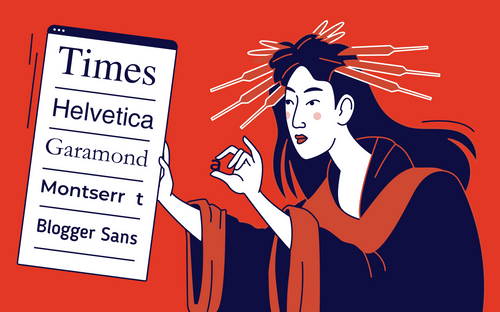
Какой шрифт лучше для чтения
Лучшие шрифты для чтения на электронной книге eBook
При чтении электронных книг приходится проводить много времени уставившись в экран. Поэтому внешний вид текста имеет большое значение! Правильный выбор шрифта может улучшить общее впечатление от чтения. Какой шрифт поможет вам читать быстрее и меньше напрягать глаза? Когда речь заходит о шрифтах, выбор очень велик. Некоторые шрифты приятны для глаз, некоторые обладают индивидуальностью, а некоторые легко читаются.
Если в вашей электронной книге много текста, самыми удобными для чтения будут шрифты с засечками, такие как Times New Roman, Garamond, Baskerville и Caslon. Эти старые традиционные шрифты уже давно используются для книг и по-прежнему являются отличным выбором для электронных книг. Важно, чтобы шрифт был удобен для чтения, тем более что люди будут читать его в цифровом формате на экранах любого размера. Шрифты с засечками более разборчивы и привлекательны для читателя.
Вот несколько лучших шрифтов, которые эксперты рекомендуют для электронных книг.
Какой шрифт лучше для чтения
Видео про саккады
Шрифты с засечками и без засечек одинаково «держат» строку
Хотя тут есть подвох. В тесте использовался шрифт 128 pt. Это в десять раз больше, чем в обычной книге, и, возможно, исследование не очень корректно применять к обычному процессу чтения.
Детские азбуки с первой страницы Гугла
Ученые взяли 80 детей 10 лет и 80 детей на два года старше, попросили их найти в тексте нужное слово (скрининг-тест) и измерили, как быстро у детей получилось это сделать.
Контрольной группе оба раза давали одинаковый шрифт, а экспериментальной — сначала шрифт с засечками, а потом без
Предпочтения же людей вообще однозначные: топ-3 шрифтов и у дислексиков, и у недислексиков — без засечек.
Разные типы сглаживания
Знаменитые дизайнеры vs научные исследования про читаемость шрифтов
Я работаю дизайнером около 10 лет. В дизайне не очень много объективных и проверяемых законов, и когда мне нужно было что-то выяснить, я искала информацию в профессиональных книгах, блогах крутых ребят, спрашивала у знакомых арт-директоров и приставала к людям в коридорах.
А потом узнала, что ученые уже сто лет как выяснили то, про что до сих пор спорят дизайнеры.
Мы в Тинькофф сравнили мнение знаменитых дизайнеров и ученых о том, какие шрифты легче читать: антикву(с засечками) или гротески(без засечек).
Почему я вообще этим занялась
Однажды мне нужно было написать инструкцию для джунов о том, как выбрать шрифт. Я написала, что для больших текстов лучше использовать шрифты с засечками, потому что глаза меньше устают от такого шрифта и засечки помогают держать строку.
Потом пришел редактор и откомментил: «Пруфы?»
«Да это же очевидно», — подумала я и открыла «Википедию»:
В «Википедии» пруфов не было, и я пошла к книжному шкафу.
На мой взгляд, шрифт с засечками меньше утомляет при долгом чтении обычных, «бумажных» изданий, чем гротеск, по двум причинам. Во-первых, засечки подчеркивают окончания штрихов, становясь дополнительными «смыслоразличителями». Во-вторых, буквы с засечками несколько сложнее по форме, поэтому сильнее отличаются друг от друга, чем гротесковые. А наш читательский глаз больше нуждается в балансе индивидуальности и унификации, чем дизайнерский, который радуется зеркальной вылизанности.
Юрий Гордон «Книга про буквы от Аа до Яя», Откуда взялись и зачем нужны засечки, стр. 51
Шрифт без засечек только кажется простейшим. Его форму специально упростили для детей, а взрослым его читать труднее, чем антикву, ведь ее засечки служат не только для украшения.
Ян Чихольд «Облик книги», О типографике, стр. 21
Ян Чихольд
Ну ладно, старинные мастера опирались на чутье, но, может, кто-то посовременнее объяснит с пруфами?
Сергей Сурганов, арт-директор «Медузы», дизайнер Notion:
Используйте шрифт с засечками для длинных текстов
Когда вы оформляете любой длинный текст (статью, резюме, письмо, инструкцию), стоит использовать шрифт с засечками, то есть антикву. Считается, что длинный текст, набранный таким шрифтом, легче читать. В традиционной книжной верстке тоже используются именно антиквы, поэтому если вы делаете что-то похожее, то выбор ясен.
Инструкция арт-директора «Медузы» Сергея Сурганова «Как выбрать шрифт»
Короче, у нас три довода:
«согласно общепринятому мнению»,
«на мой взгляд»,
«считается»,
…
Книги не помогли, и я попробовала разобраться с помощью научных статей, есть ли какие-то доказательства, что шрифт с засечками легче, быстрее или приятнее читать, чем шрифт без засечек. Конечно, это не полноценный научный обзор. Но лучше, чем «согласно общепринятому мнению». Ссылки на статьи есть в конце каждого раздела.
Наконец, несмотря на то, что исследование не включало ни одного акцидентного шрифта, есть некоторые плохие шрифты. Держитесь от них подальше, потому что они могут значительно снизить скорость чтения текста на сайте. И даже с использованием хороших шрифтов избегайте мелкого текста и низкой контрастности, которые сильно ухудшают восприятие контента.